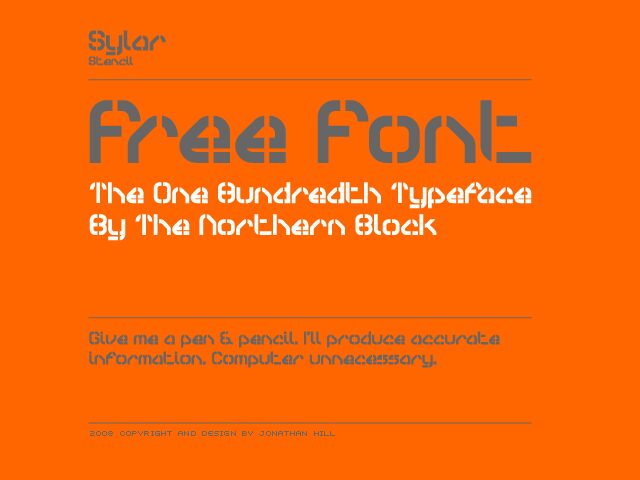
Sylar Stencil von Jonathan Hill ist eine kostenlose, futuristische Stencil-Display-Schrift mit einem scharfen, modularen Rhythmus. Die Buchstaben wirken wie aus einer eleganten industriellen Hülle geschnitten, eine Mischung aus abgerundeten Ecken, winkligen Kerben und offenen Stencil-Unterbrechungen, die den Wortformen einen prägnanten Sci-Fi-Puls verleihen.
Damit eignet sie sich perfekt für Game-Branding, Tech-Poster, Flyer für elektronische Musik, Titelkarten, Verpackungen und kurze Headlines, bei denen die unterbrochenen Formen die Stimmung allein tragen können. Als kostenlose Schrift funktioniert sie am besten in kurzen Display-Anwendungen, insbesondere bei Logos und Überschriften, die ihren technisch-robotichen Charakter unterstreichen.
Sylar Stencil